¿Una mano con el clásico "cual es esta tipografía"?
Hola, ya sé lo cansino que puede ser utilizar este subforo para este menester, pero llevo bastante loco buscando el nombre de esta fuente y todo a raiz de que llegara a mis manos un catalogo de tipos Richard Gans. Me ha sido imposible localizarla por el nombre por el que aparece en el catalogo.
La imagen está sacada de un articulo de unostiposduros a propósito de la fundición.
Ya me he quemado todos los buscadores de fuentes sin ningún resultado valido. Y ya tengo ganas de usar a esta desconocida me parece una pasada.
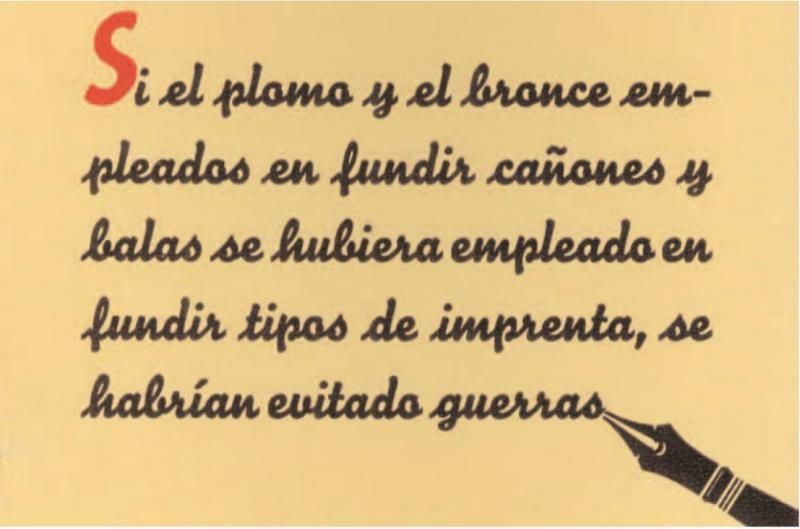
Seguro que conoces WhatTheFont, pero por si acaso te dejo aqui el resultado que me ha dado a mi. Algunas son bastante similares :( Espero que algo te pueda ayudar.
Gracias por la mano :). Pero parece que hay un problema con el link y aunque me lleva a la pagina me reporta error. Pues desde luego que lo intentado varias veces con whatthefont pero no me habia dado nada similar.
Ya le he vuelto a dar la vuelta otra vez a whatthefont, y aunque sin resultado me he dado de bruces con otro ejemplo de esta tipo. Es de otro catalogo de Gans.
Buscando, también me salen sus manuales... es posible incluso que no exista una tipografía "tal cual", pero sí familias que se le parezcan bastante...
Bueno, revisando esa sección no veo realmente ninguna, sorry, quizá opiné demasiado deprisa. Las veo demasiado ligeras y la que tú enseñas parece ser mucho más redonda. Échale un ojo de todos modos a la web, por si acaso algo te cuadrara.
http://luc.devroye.org/fonts-39175.html aquí he visto varios links a tipografías de la Fundición de Gans.
Y si haces scroll, muchos ejemplos. Quizá por ahí...
Al final de los finales me conformé con otra fuente relativamente cercana a esta. (ahora mismo no la tengo disponible, en cuanto vuelva al curro la cuelgo aquí).